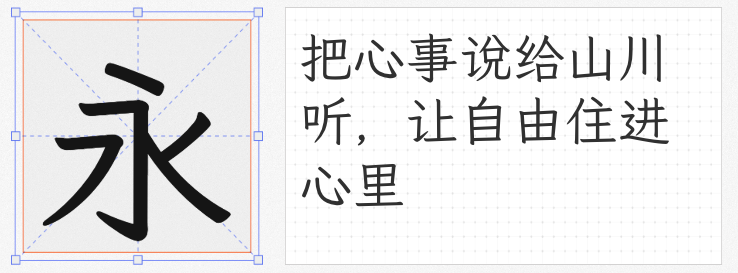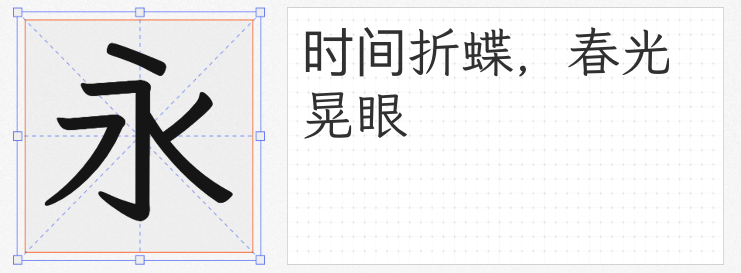
在儿童服装设计领域,字体的选择不仅是品牌调性的延伸,更是与目标受众建立情感连接的关键。以下四款免费商用字体凭借独特的设计语言与文化内涵,成为儿童服装视觉传达的理想选择。
这款由阿里巴巴团队开发的黑体字,以方正饱满的体态和现代感十足的布白设计脱颖而出。其笔画处理在“图形感”与“书写感”之间实现精妙平衡:直角笔型强化硬朗质感,粗壮均匀的线条确保信息层级清晰,而笔画间的巧妙断开设计则赋予字体灵动呼吸感。在儿童服装设计中,数黑体尤其适合作为主标题或价格标签字体——厚实的笔画能瞬间抓住视线,而活泼的细节处理(如字母“O”的圆形开口)又与童趣主题天然契合。
以爨宝子碑为灵感源头的阿里妈妈刀隶体,通过机器学习将隶书方笔与楷书结构融合,创造出极具张力的视觉语言。三角点折弯与“雁尾”横画的设计,让字体如孩童涂鸦般稚拙倔强;看似失衡的布白与中宫处理,实则暗含“险中求正”的书法智慧。这款字体适合用于儿童服装的图案印花或文化主题系列设计,其打破常规的结构能激发想象力,而隶书基因又赋予作品历史厚重感,形成传统与现代的有趣对话。
作为开源字体Klee One的衍生版本,彭蠡文楷以《古籍印刷通用字形规范表》为基准,对14,250个汉字进行系统性整理。其设计既保留了楷书的端庄秀丽,又通过部件统一化处理提升现代适用性。在儿童服装设计中,这款字体特别适合传统文化主题或国潮风格产品——规范的字形结构确保信息可读性,而源自古籍的笔意韵味又能传递文化底蕴,形成视觉与内涵的双重吸引力。
基于多款日文字体衍生的千菅书体,以日标字形优先显示为特色,完美适配中日文混排场景。其笔画设计融合仿宋的纤细与楷书的圆润,形成独特的“教科书体”风格。在儿童服装设计中,这款字体尤其适合双语品牌或国际童装系列——清晰的字形结构便于儿童识读,而日式设计特有的清新感则能营造温馨氛围,特别适合印在T恤、卫衣等日常款式的胸前位置。